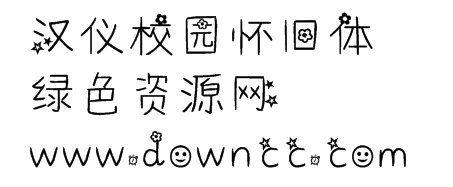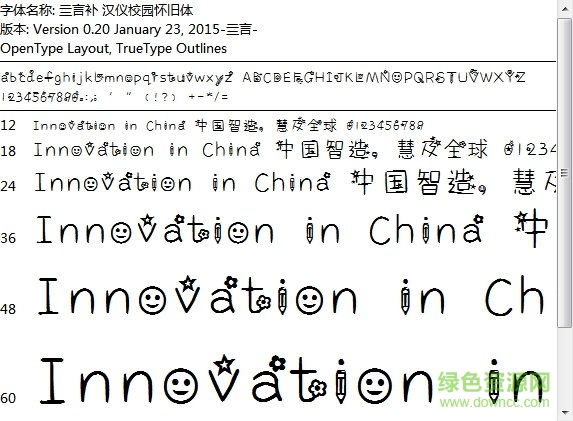
漢儀校園懷舊體是一款可愛好看的卡通字體,增加了各種點綴,讓文字間充滿童真童趣和校園元素的特色美感,顯得更加有趣和生動,快來綠色資源網(wǎng)試試吧!
漢儀校園懷舊體出自漢儀字庫,增加了諸如或多鉛筆、紙飛機(jī)、星星燈各種卡通圖案,增加了文字內(nèi)容的校園格調(diào),更顯朝氣蓬勃。
漢儀校園懷舊體是微博博主三言在原來的基礎(chǔ)上補(bǔ)充而來,完善了字體,給文字美化修飾,讓其的使用更加廣泛,對用戶的平面設(shè)計、包裝設(shè)計也帶來不錯的使用體驗!